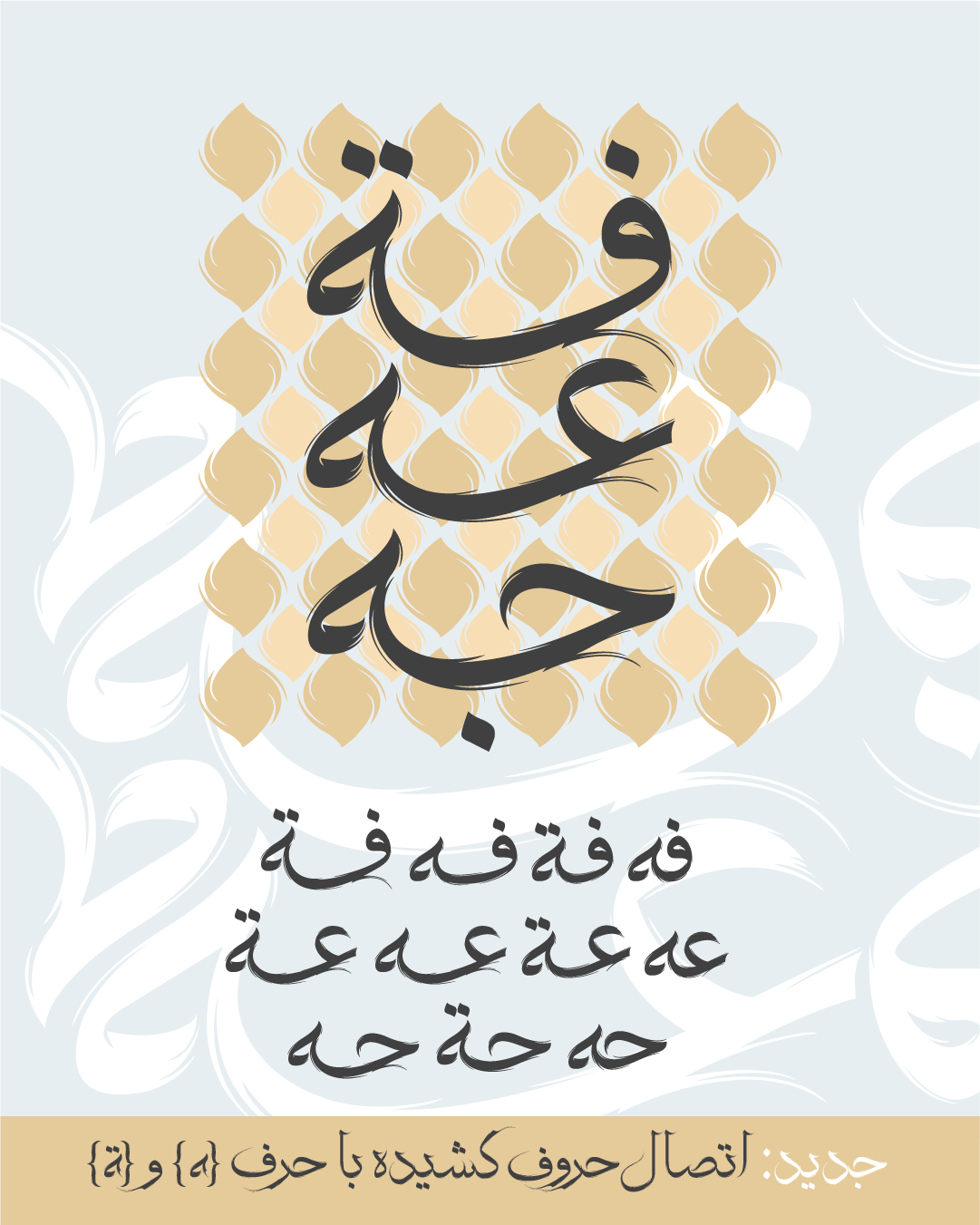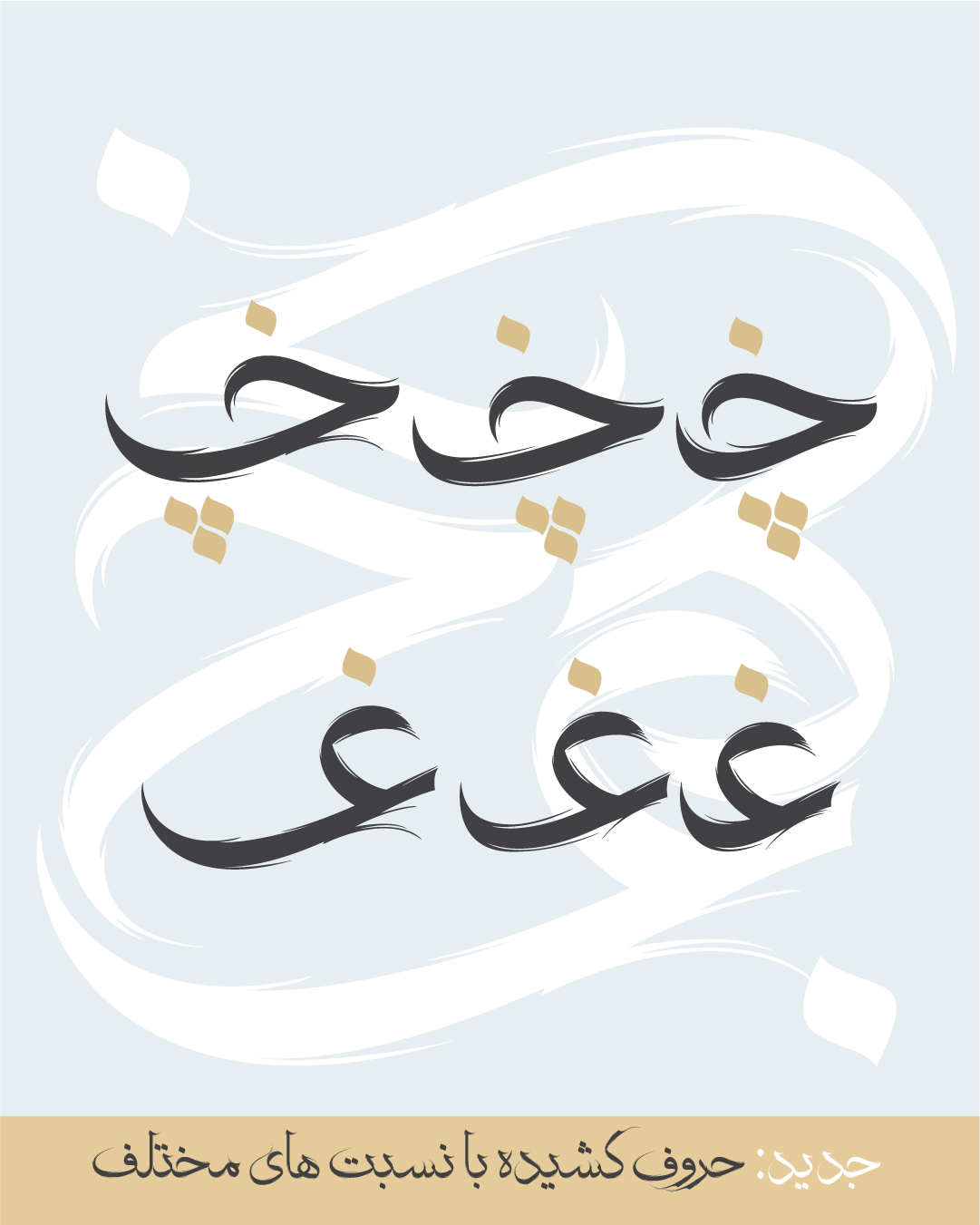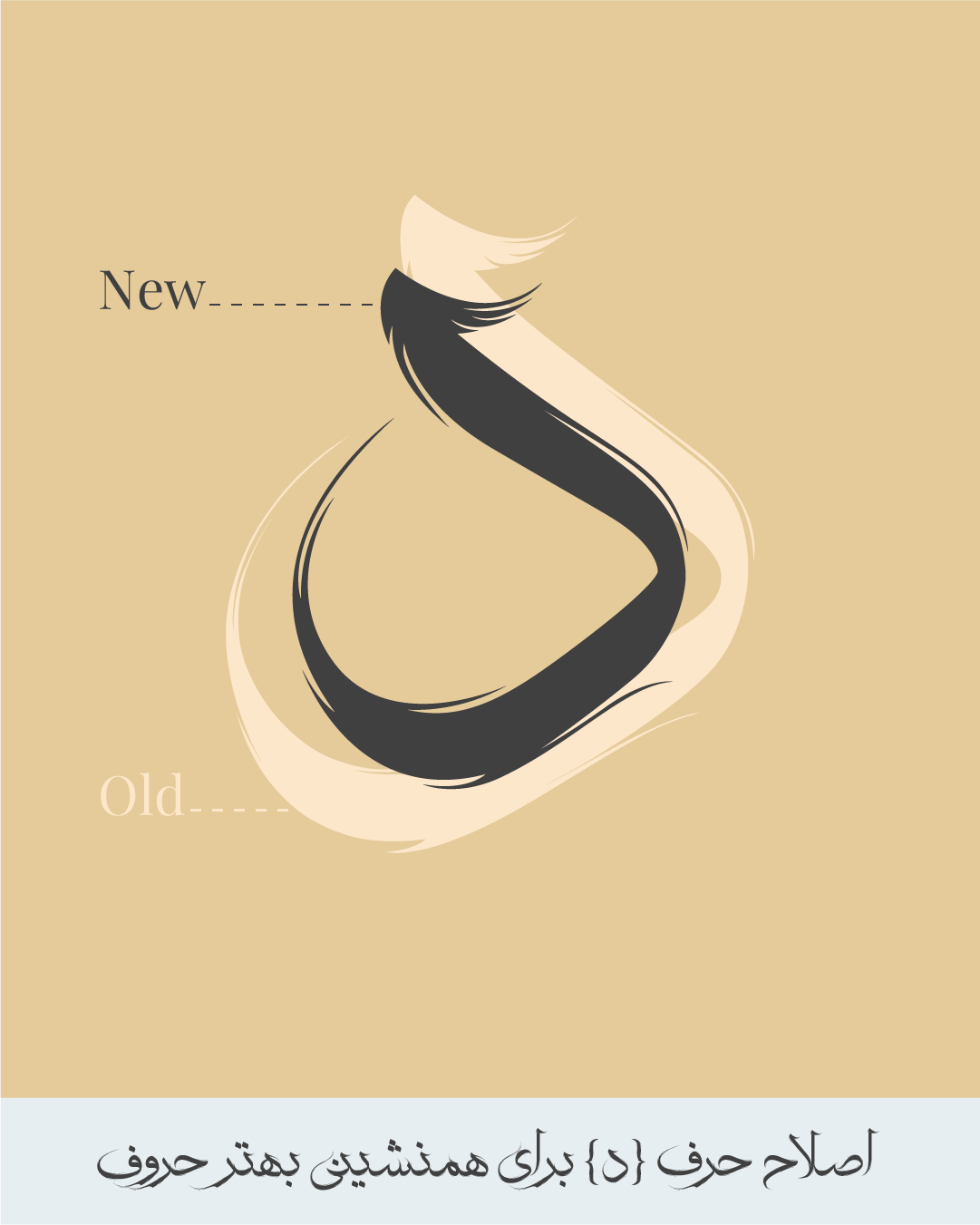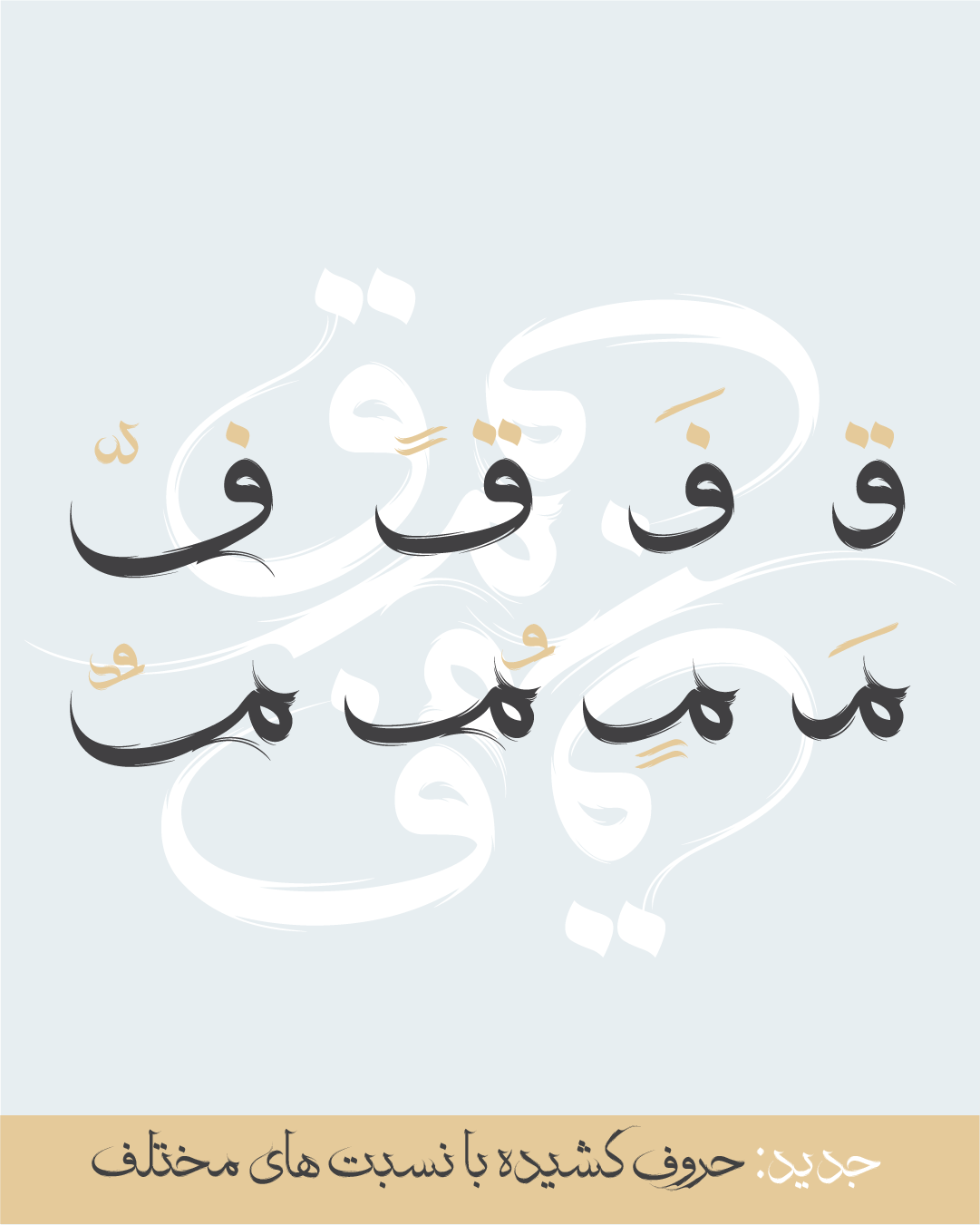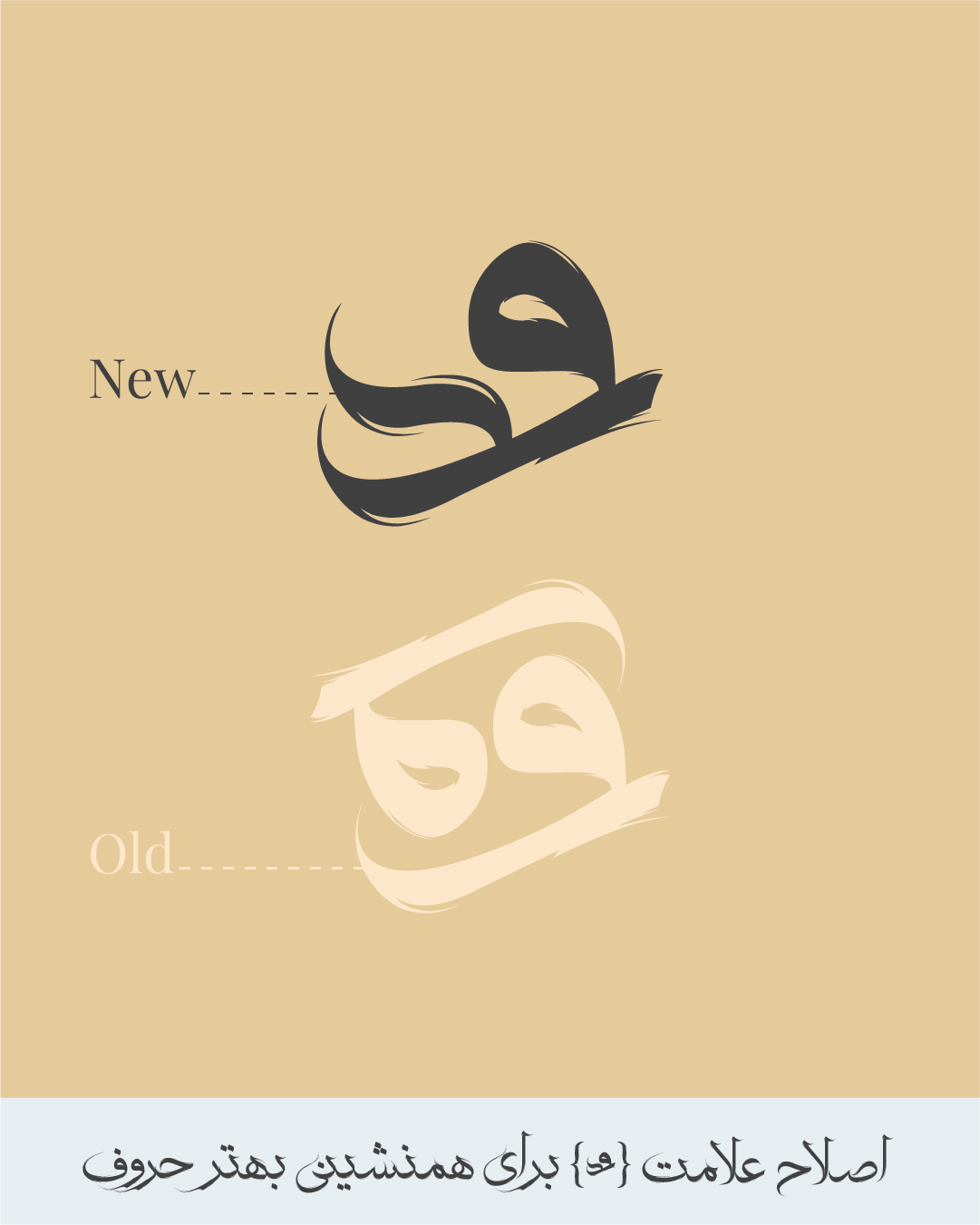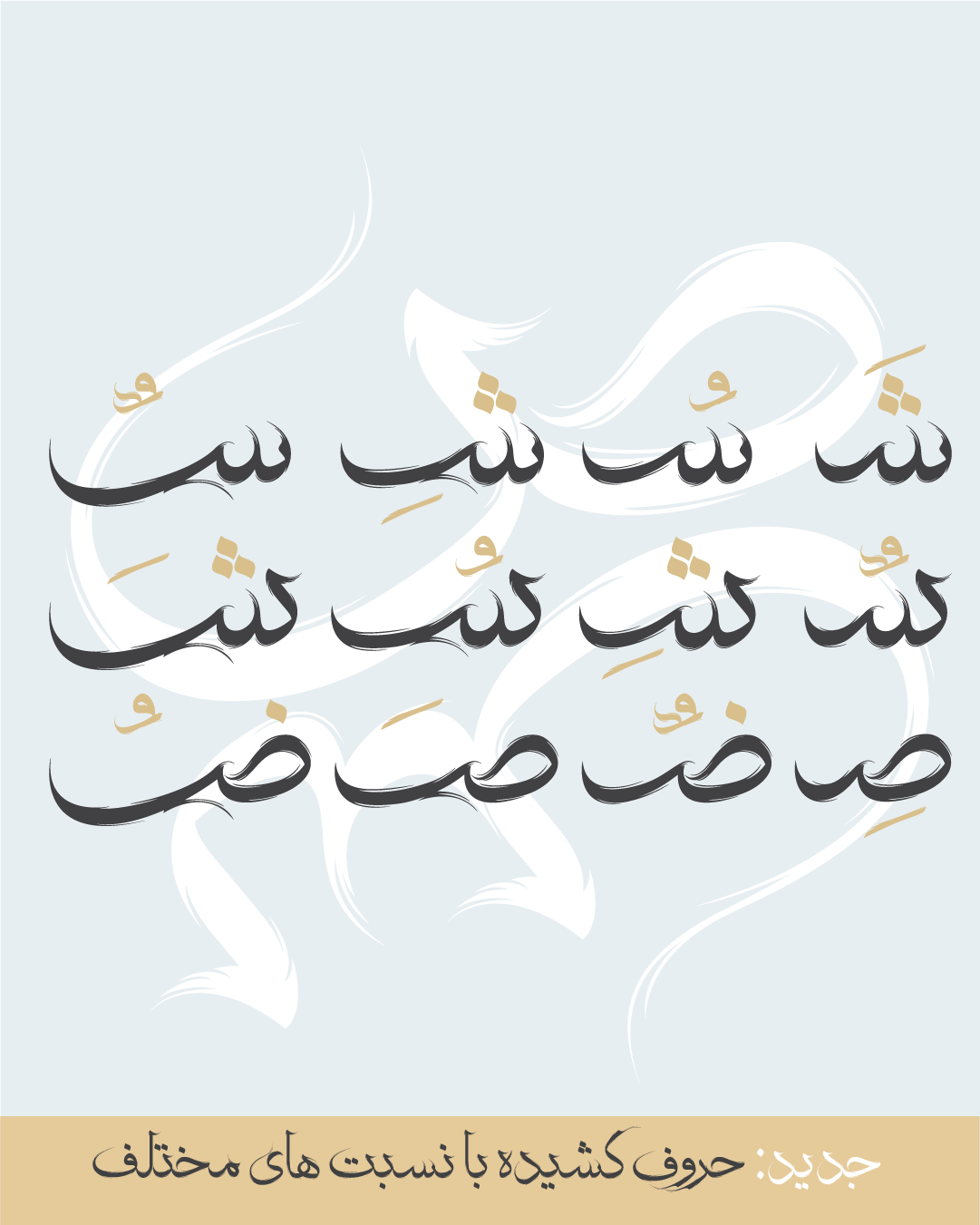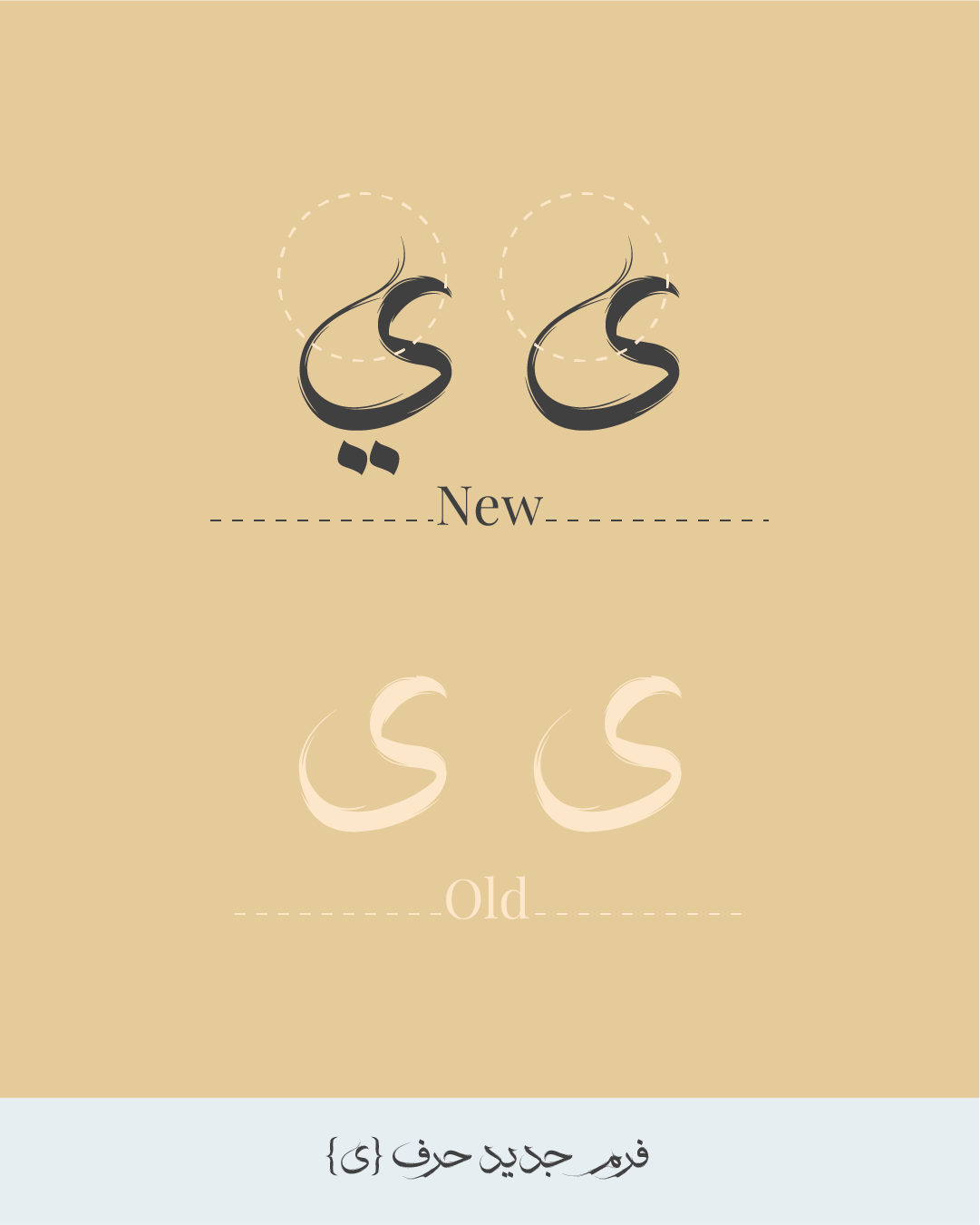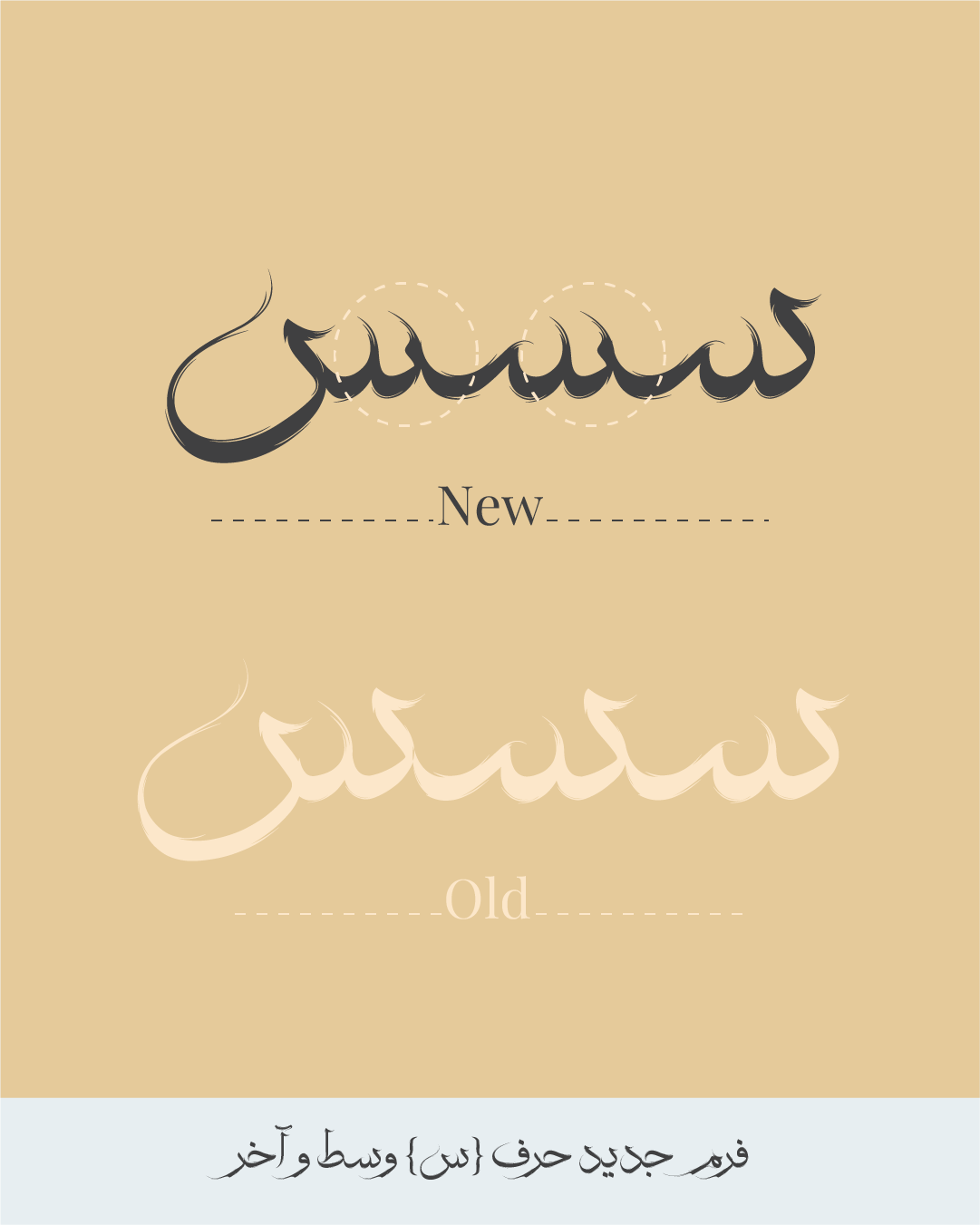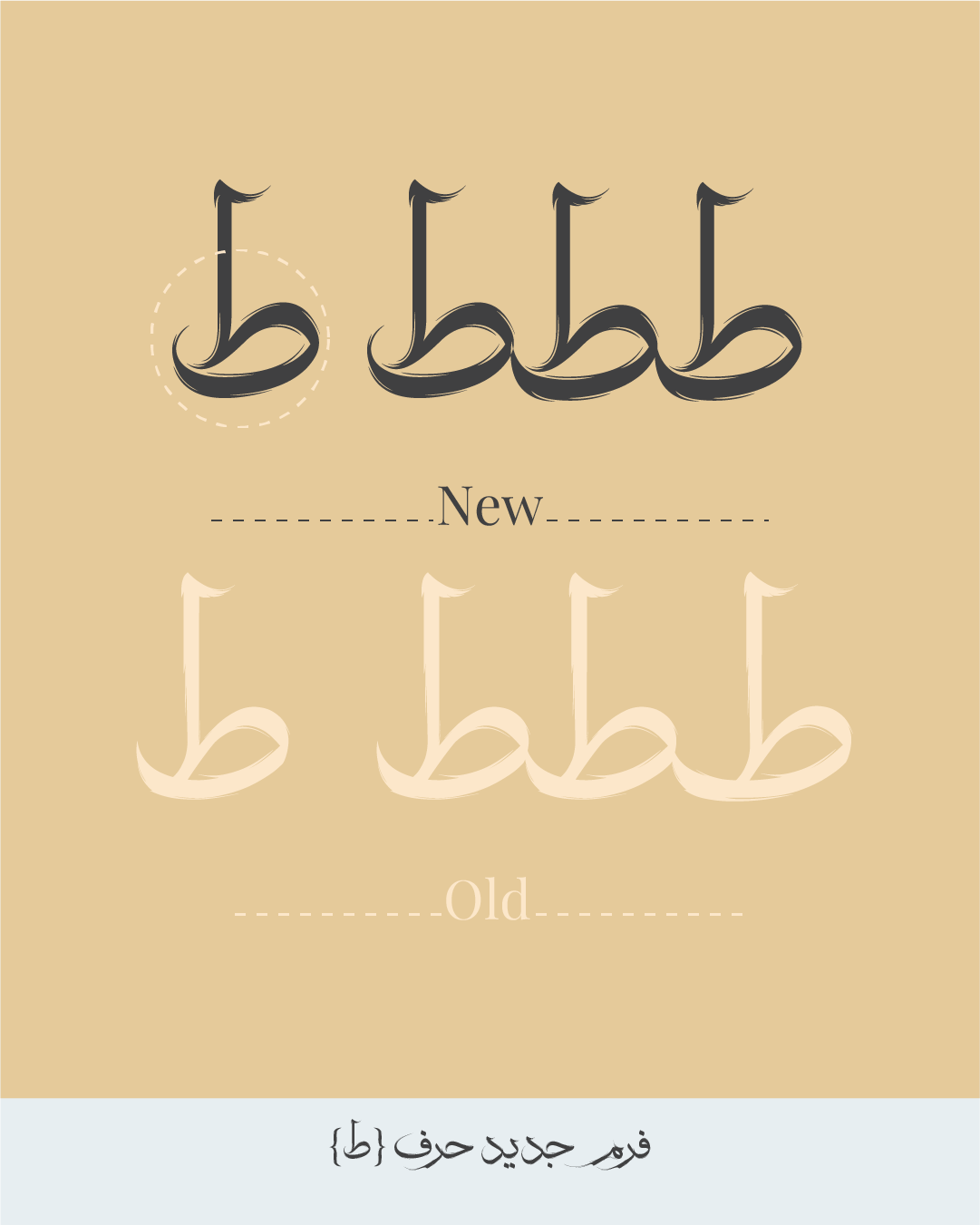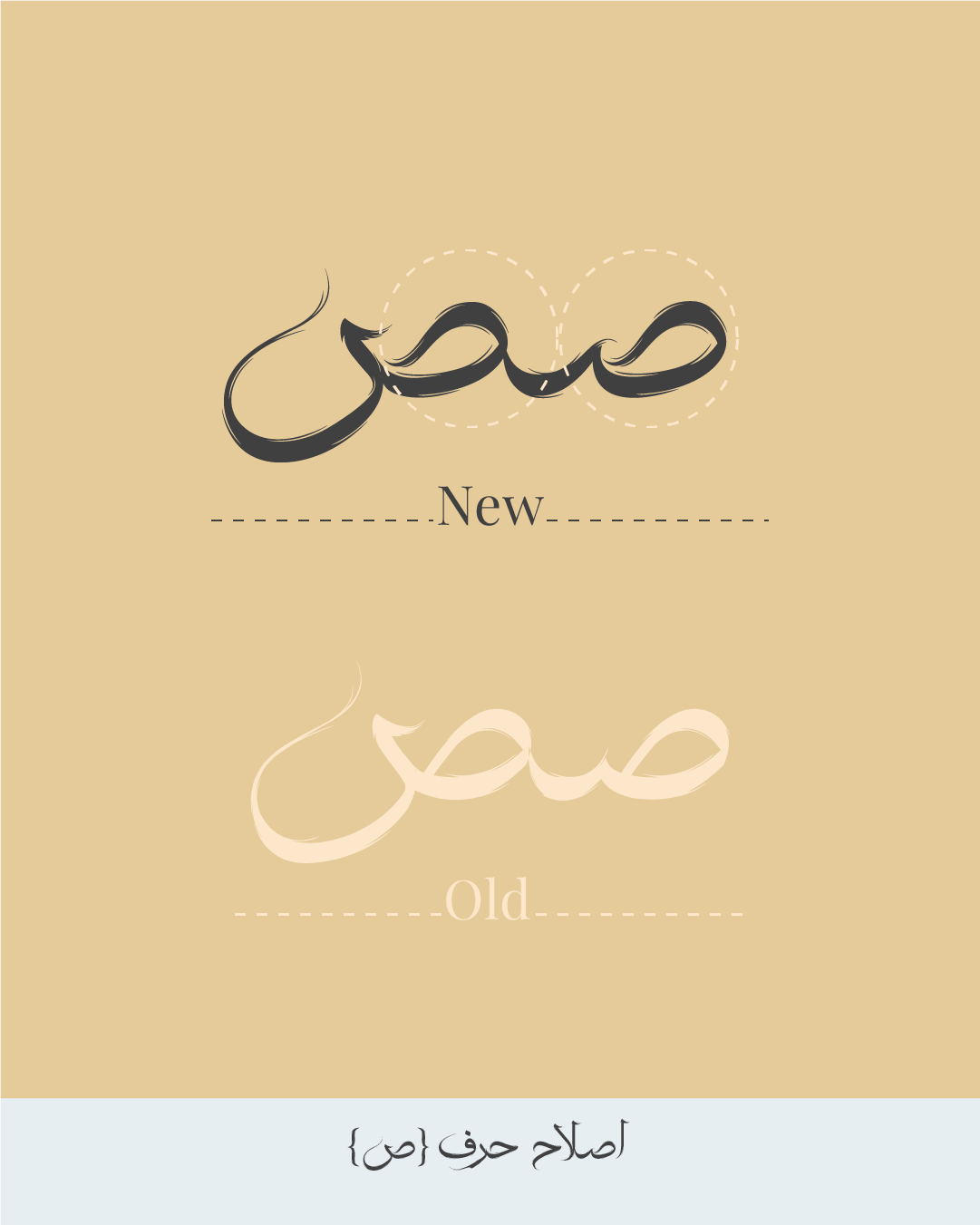
در نسخه‌ی 2 فونت رهروان چه تغییراتی می‌بینیم؟
در این نسخه بازنگری کلی در فرم حروف و شکل نقطه‌ها انجام شده است. علاوه بر این، پشتیبانی از زبان عربی نیز به این نسخه اضافه شده است.
1.  اصلاح فرم حرف "د" برای ایجاد هماهنگی و همنشینی بهتر حروف
2.  اصلاح علامت ( ٌ )
3.  بازنگری فرم حرف (ی) و (ي)
4.  طراحی فرم جدید حروف ( س ) میانی و پایانی متصل
5.  باز طراحی حرف ( ط ) و ( ظ )
6.  باز طراحی حرف ( ص ) و ( ض )
7.  اصلاح فرم حرف ( ک ) و ( گ )
8.  تعریف فرم دوم حروف ( ا ) و ( آ )
9.  تعریف فرم دوم ترکیب ( لا )
10. طراحی فرم های جایگزین برای حروف ( ب ، پ ، ت ، ث ، ن ، ط ،  ظ ، ح ، ج ، چ ، ح ، خ ، ع ، غ ) با یک و دو کشیدگی
11. جایگزین برای حروف ( ه ، ل ، م، س ، ش ، ک ، گ ، ف، ق ، ص ، ض) با یک ، دو و سه کشیدگی
12. طراحی فرم های جایگزین برای اتصال حروف کشیده به حروف ( ا ، ی ، ي ، ه ، ة )
13. طراحی اعداد عربی 4، 5 ، 6
14. اصلاح فرم حروف عربی